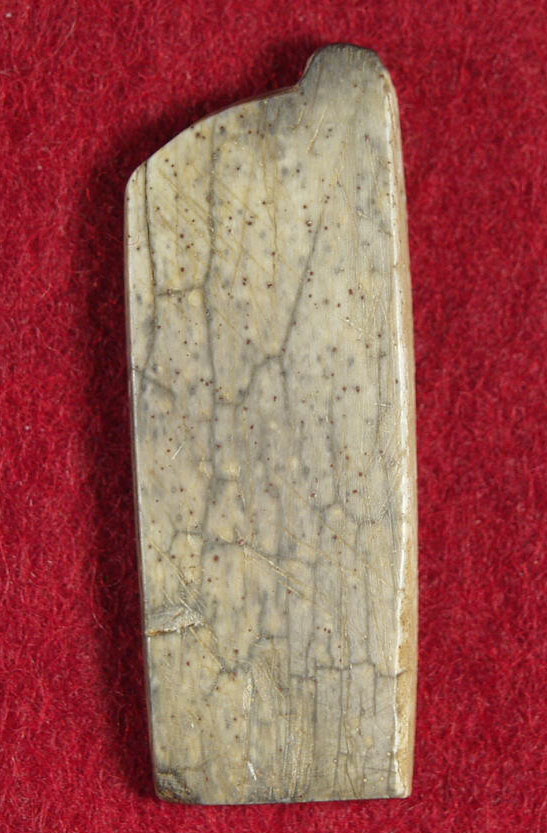
| 資料名 | 石刻タブレット |
| 文字/言語 | ヒエログリフ/古代エジプト語 |
| 材質/形態 | 石/タブレット |
| 管理/所蔵 | 古代文字資料館/個人蔵 | 古代エジプトの神聖文字(ヒエログリフ)が刻された石版。 半分に意図的に切られているようにみえる。上には紐を通す穴がある。 中央に王名(アメンヘテプ三世)を表すカルトゥーシュ(縄の枠)があるから、古代エジプト新王国時代(前1400頃)のものということになるが、真贋は不詳。 |